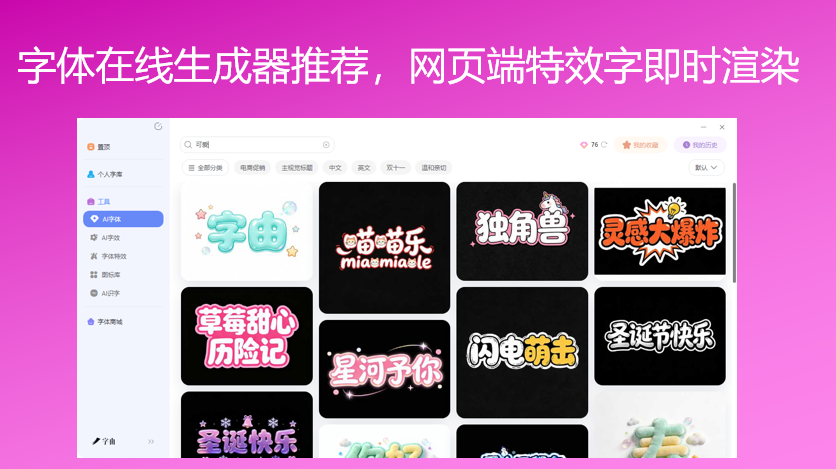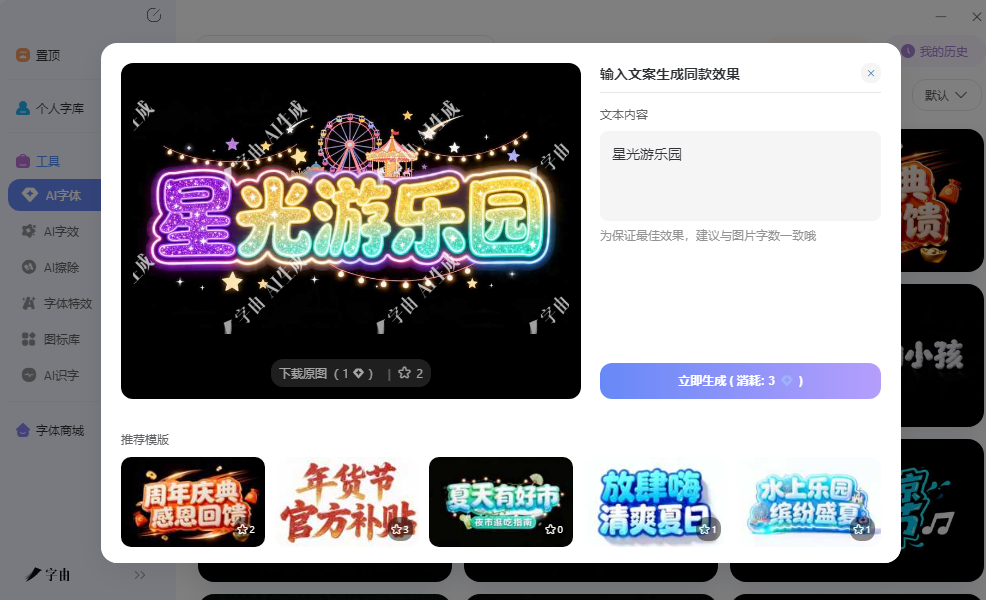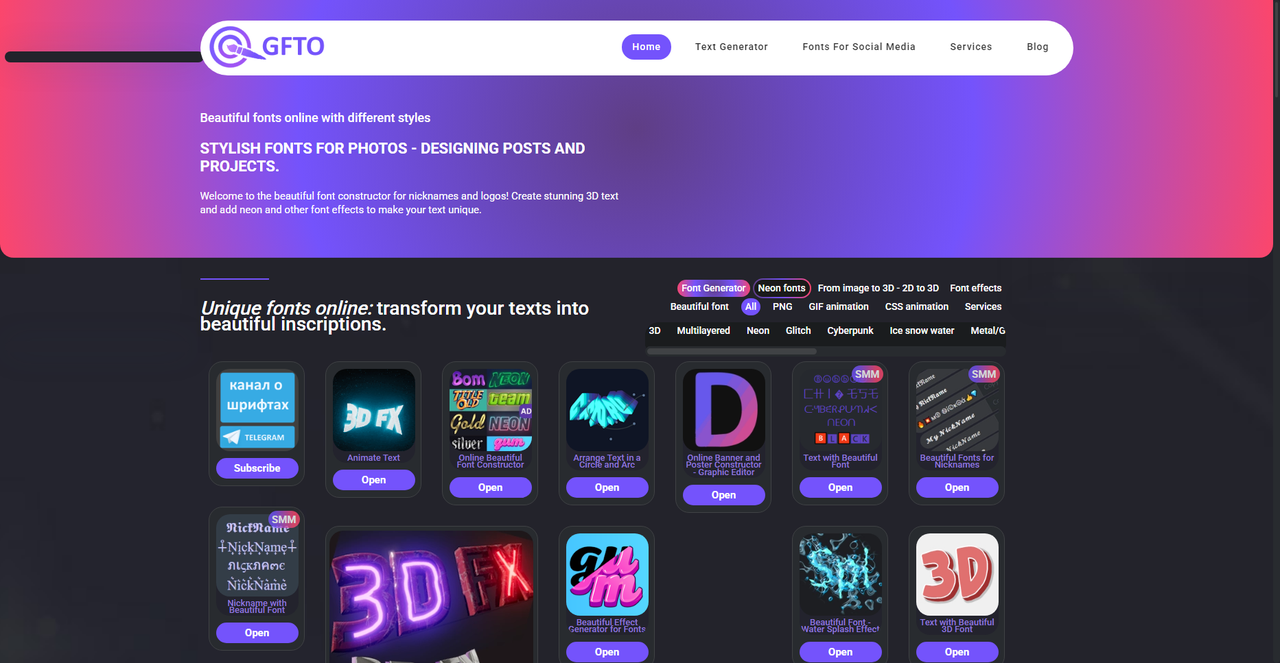
字体在线生成器推荐,网页端特效字即时渲染
做海报标题时,很多人不会用PS的图层样式,做出来的文字总是平平淡淡。去网上搜教程学做金属字,看完视频自己操作还是一团糟,最后放弃用回默认字体。其实现在不少网页工具专门解决这个问题,打开浏览器输入文字就能生成带特效的艺术字图片,几分钟出一张带透明背景的PNG,直接拖进设计软件继续排版。这篇文章整理的几个生成器,有的专攻金属质感,有的擅长发光效果,有的支持涂鸦风格,还有的提供多种材质特效模板。
字由在字体生成这个方向上有AI字体功能,和单纯下载现成字体不太一样。这个功能的核心是把你上传的手写样本或者选择的风格参考,通过深度学习模型转换成一套完整的字体风格渲染图。上传几张自己写的字拍照上传,系统会分析笔画特征、连笔习惯和字间距偏好,生成带有你个人风格的字体效果。生成的是PNG图片,带透明背景,可以直接放进海报、PPT或者社交媒体配图里。
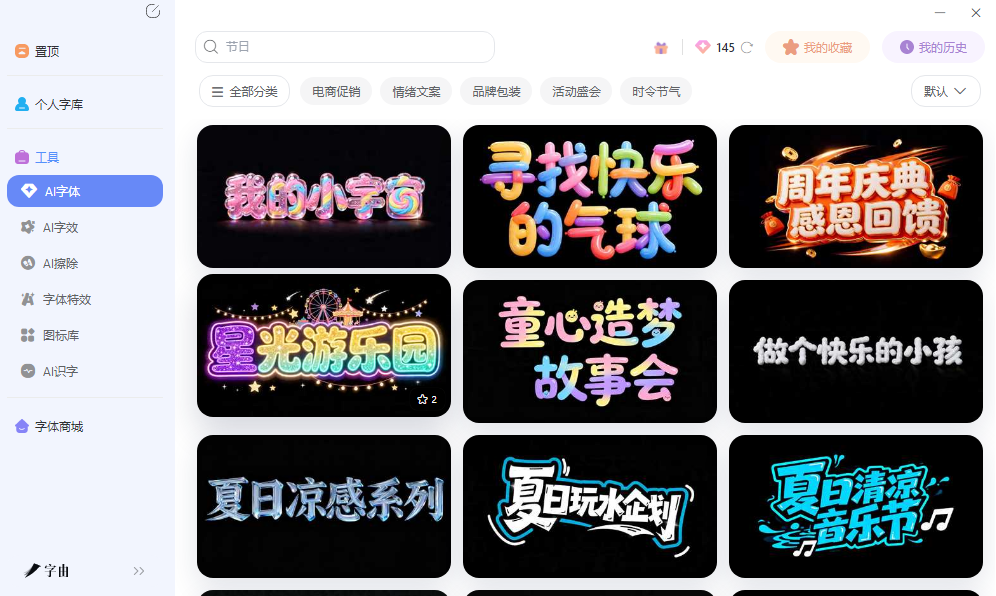
对于想做个人品牌但预算有限的人来说,这个方式比请设计师做定制字体便宜得多,也省去了学习专业字体设计软件的时间。不需要懂贝塞尔曲线或者字重计算,上传字迹就能出图,门槛降低了不少。生成的字体风格可以保留手写痕迹,笔画粗细变化和连笔特征都能还原,比单纯的手写体字体更有个人特色。
字由的AI字体不是生成字体文件,而是生成带透明背景的图片。这意味着改文案需要重新生成,但优势在于效果精致,适合做标题或者Logo这种不需要频繁改动的场景。和网页生成器相比,字由的AI字体基于你的真实笔迹,风格独特性更强,不是套用现成模板,而是真正属于你的字体风格。
2、Engfto
Engfto是一个综合性的在线文字特效平台,模板库覆盖了金属、火焰、冰晶、木纹、大理石、皮革等几十种材质效果。选择模板后输入文字,可以调整主色、辅色、光影角度、表面纹理、文字间距等参数,生成高分辨率的PNG图片。网站支持中文输入,部分模板对中文字符的渲染效果不错,笔画细节处理比较到位,做中文海报时不会出现笔画粘连。
3、AI Graffiti Generator
AI Graffiti Generator是一个基于AI的涂鸦风格文字生成工具。输入文字后,系统会分析内容并生成带有涂鸦喷绘效果的图片,包括墙面喷涂、马克笔手写、贴纸拼贴等多种风格。每种风格都有独特的笔触质感和色彩处理方式,比如墙面喷涂带有颗粒感和滴落效果,马克笔手写则有粗细变化和连笔特征,贴纸拼贴则是多块彩色贴纸组合成文字形状。这个工具对做街头文化主题、音乐节海报或者潮流品牌物料的设计师很实用。传统涂鸦字体设计需要手绘功底,AI Graffiti Generator通过机器学习模型模拟了各种涂鸦技法,输入文字就能出图,省去了手绘时间。生成结果可以下载高分辨率PNG,带透明背景,直接放进海报或者T恤设计稿里。
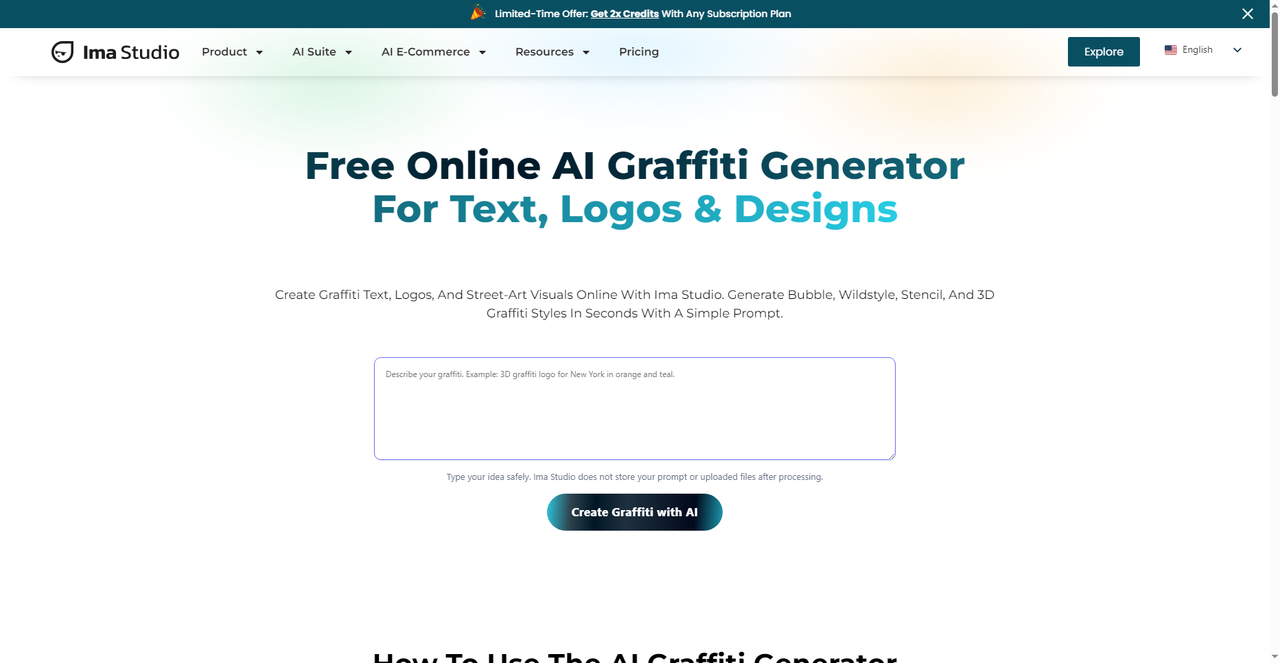
4、Glow Text Generator
Glow Text Generator专注做发光效果的文字,包括霓虹发光、光晕扩散、脉冲闪烁等多种风格。输入文字后选择发光类型,调整光晕颜色、扩散范围和强度等级,系统会实时生成预览图。霓虹效果适合夜店海报和电竞主题,光晕效果适合浪漫氛围和节日贺卡,脉冲效果适合科技感的设计项目。颜色选择比较自由,除了预设的几种常见配色,还可以手动输入色值,匹配品牌VI或者项目主色调。
网站支持调节发光层的叠加方式,内发光和外发光可以分别控制,做出从轻微光晕到强烈霓虹的各种效果。生成结果可以下载PNG图片,透明背景,直接拖进设计软件里继续排版。
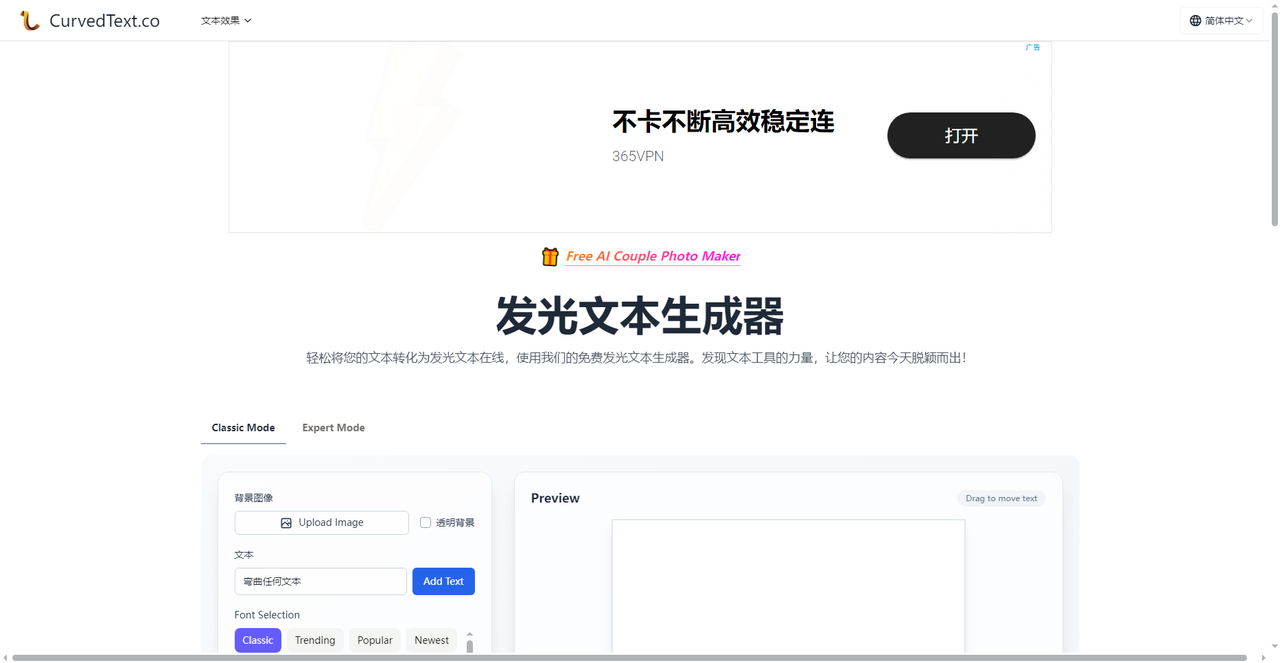
5、Metal Font Generator
Metal Font Generator是一个专门做金属质感文字的在线工具。进入网站后输入文字内容,选择金属风格模板,系统会实时渲染出带金属光泽和反射效果的文字。可以调整金属类型,比如黄金、铬合金、生锈铁、古铜等,每种金属的光泽度和反射强度都不一样,做出来的质感差别很明显。黄金效果适合奢华主题,铬合金适合科技风格,生锈铁适合复古主题,古铜适合文艺主题。
网站的操作界面比较简洁,文字输入框在上方,参数调节面板在下方。除了金属类型,还可以调整表面纹理、倒角深度和光源方向,拖动滑块实时就能看到变化,这种所见即所得的调节方式比输入数值更直观。生成结果支持下载PNG图片,带透明背景,直接放进海报或者PPT里就能用。对于需要做金属标题但不懂3D建模的人来说,这个工具省去了学习复杂软件的时间,打开网页几分钟就能出图。网站不需要注册账号就能使用基础功能,打开即用,试错成本很低。
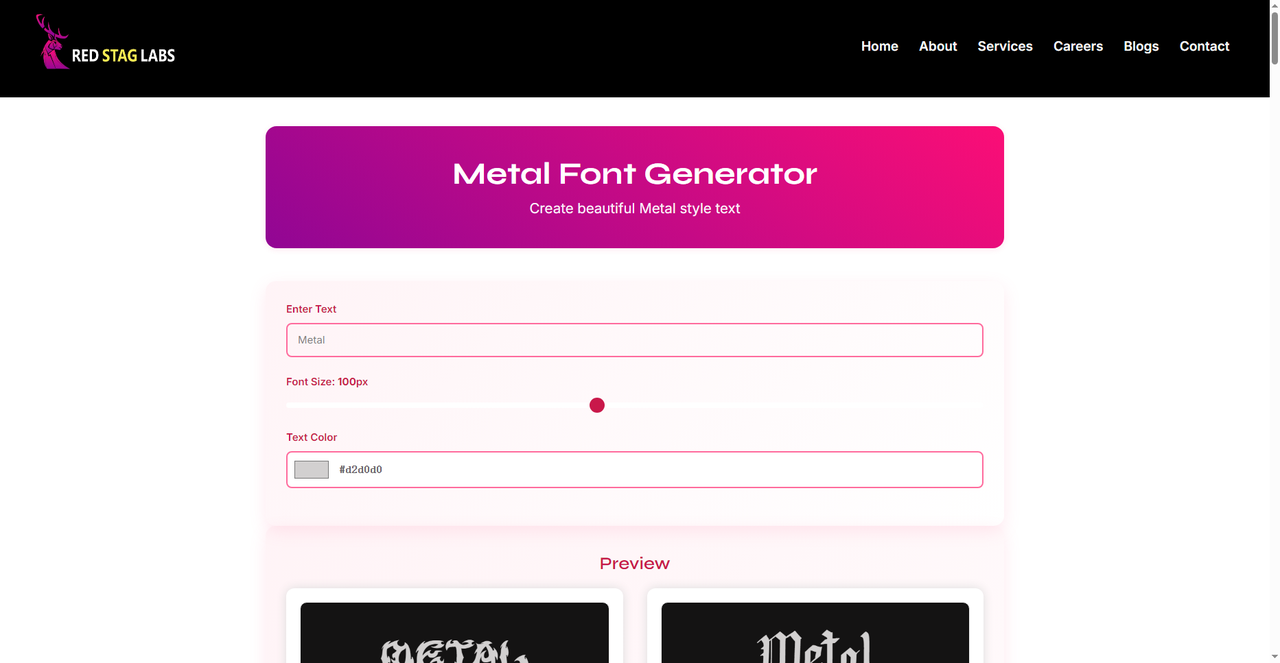
Metal Font Generator的金属质感适合高端商务和复古主题,Glow Text Generator的发光效果适合夜生活和科技风格,AI Graffiti Generator的涂鸦风格适合潮流和街头文化,Engfto的模板库覆盖面广,各种材质都能找到。字由在字体管理和即时调用方面比较省心,从选字体到在设计软件里使用都能在客户端内完成。